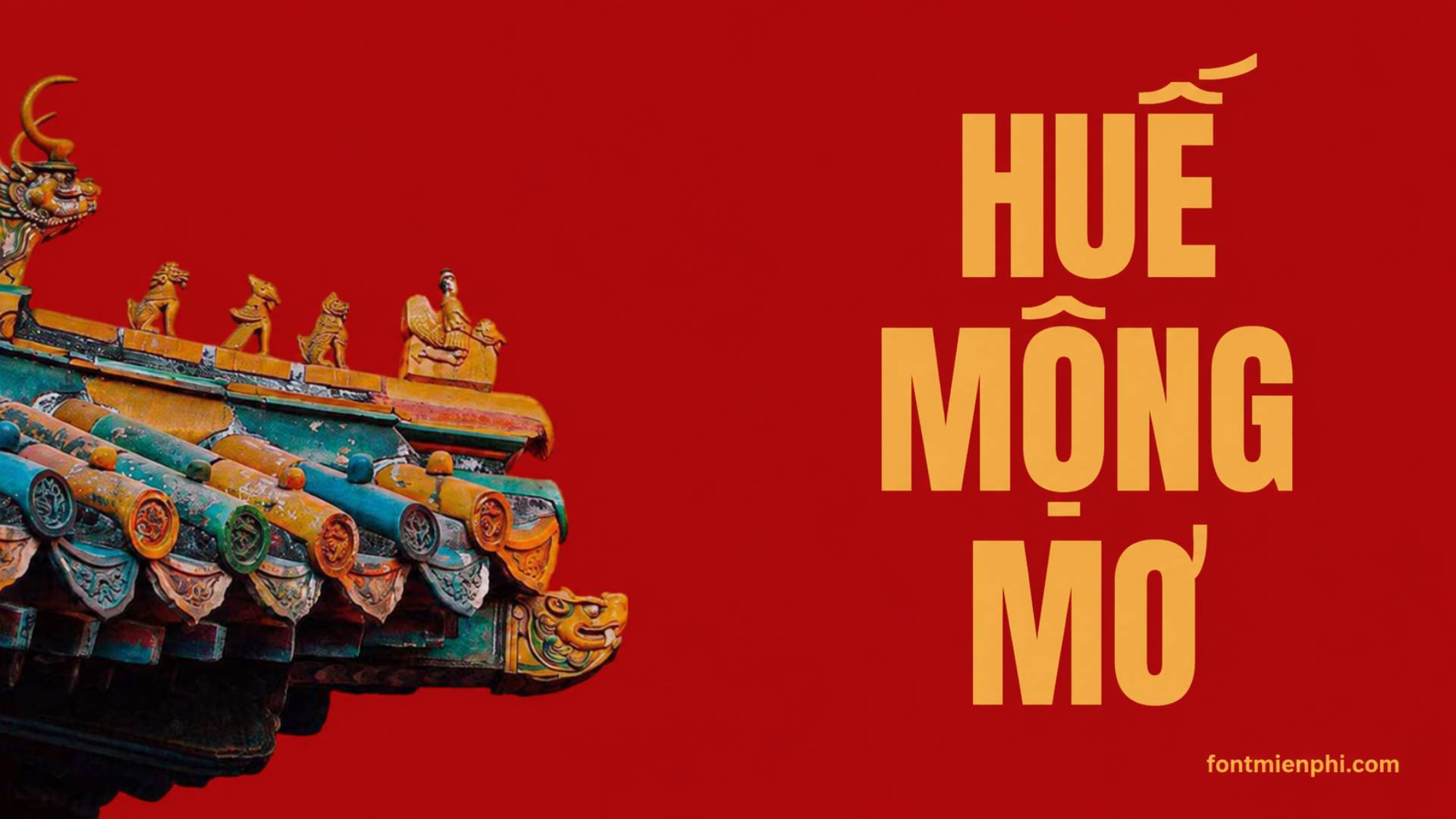
Font việt hoá PS Anton
Tải Font Việt Hóa PS Anton – Nét Chữ Mạnh Mẽ Cho Các Thiết Kế Đột Phá
Nếu bạn đang tìm kiếm một phông chữ béo, đậm và mang lại sức nặng thị giác tuyệt đối cho các tiêu đề lớn, thì Font Việt hóa PS Anton chính là mảnh ghép còn thiếu trong bộ sưu tập của bạn. Lấy cảm hứng từ các phông chữ quảng cáo truyền thống nhưng được tinh chỉnh lại cho kỷ nguyên số, Anton mang đến một cảm giác vô cùng hiện đại, chắc chắn và thu hút sự chú ý ngay từ ánh nhìn đầu tiên.
1. Nguồn gốc và phong cách của Font PS Anton
Anton vốn là một phông chữ mã nguồn mở nổi tiếng (Google Fonts), được thiết kế bởi Vernon Adams. Đây là một phông chữ thuộc họ Sans-serif (không chân), được thiết kế theo phong cách Display – chuyên dụng để hiển thị ở các kích thước lớn.
Điểm đặc trưng của Anton là các nét chữ rất dày, khít và có form dáng hình chữ nhật đứng. Cấu trúc này giúp nó kế thừa hoàn hảo tinh thần của các phông chữ quảng cáo cổ điển (như font Impact), nhưng lại sắc nét và tối ưu hiển thị tốt hơn trên các màn hình điện tử hiện đại. Phiên bản PS Anton Việt hóa đã được đội ngũ thiết kế chăm chút lại bộ dấu, giúp các designer Việt Nam yên tâm sử dụng mà không lo lỗi typography.
2. Ưu điểm nổi bật của bản PS Anton Việt hóa
Không phải ngẫu nhiên mà Anton luôn nằm trong top các font chữ tiêu đề được yêu thích nhất. Phiên bản PS Anton Việt hóa sở hữu những điểm cộng tuyệt vời:
• Sức mạnh thị giác (Visual Impact): Trọng lượng chữ lớn (Heavy weight) giúp các thông điệp của bạn “đập” ngay vào mắt người xem. Rất khó để bỏ qua một dòng chữ được viết bằng PS Anton.
• Tối ưu hóa không gian: Dù là một font chữ đậm, nhưng do có form dáng hơi thuôn hẹp về chiều ngang (condensed), Anton giúp bạn nhồi nhét được những tiêu đề dài vào không gian hẹp mà vẫn đảm bảo độ dễ đọc.
• Dấu Tiếng Việt chuẩn xác: Các dấu câu (huyền, sắc, hỏi, ngã, nặng) cùng các ký tự đặc biệt (ă, â, ê, ô, ơ, ư) được căn chỉnh tỉ mỉ về cả kích thước lẫn khoảng cách (kerning), không bị dính vào nhau ngay cả khi gõ ở size chữ lớn.
3. Ứng dụng hoàn hảo của Font PS Anton trong thiết kế
Với bản chất là một display font đầy uy lực, PS Anton là lựa chọn số một cho các trường hợp cần sự chú ý cao độ:
Mẹo thiết kế (Design Tip): Đừng bao giờ sử dụng PS Anton cho các đoạn văn bản dài (Body text) vì độ dày của nó sẽ làm rối mắt người đọc. Hãy để nó tỏa sáng ở vị trí Tiêu đề (H1, H2) và kết hợp với một font Sans-serif thanh mảnh như Roboto hay Open Sans cho phần nội dung.
• Banner Khuyến mãi & Flash Sale: Đây là “đất diễn” tuyệt vời nhất của PS Anton. Những dòng chữ như “SIÊU ƯU ĐÃI”, “FLASH SALE 50%” được viết bằng font này trên giao diện các website thương mại điện tử sẽ kích thích tỷ lệ chuyển đổi (CTR) cực tốt.
• Thumbnail YouTube & Social Media: Giúp video hoặc bài đăng của bạn nổi bật giữa hàng ngàn nội dung khác trên bảng tin nhờ những dòng tiêu đề to, rõ và ấn tượng.
• Thiết kế UI/UX Website: Làm font chữ cho các Hero Banner hoặc các nút Call-to-Action (CTA) khổng lồ trên landing page.
• Poster & Áo thun (Typography): Phù hợp với phong cách đường phố (Streetwear), thể thao (Sports) hoặc các sự kiện âm nhạc, giải đấu game sôi động.